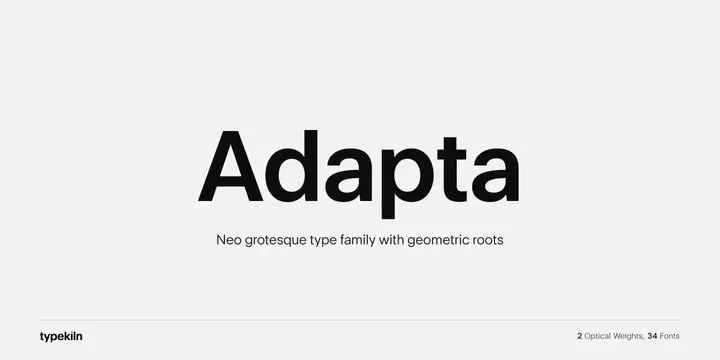
Adapta Sans Serif é uma família de fontes sans serif concebida para uso tanto em impressão quanto em produtos digitais. Esta fonte combina um estilo neutral com a elegância e personalidade únicas de formas geométricas, criando um design que transmite não apenas profissionalismo, mas também um toque acolhedor. Com uma ampla variedade de 34 tipos diferentes, incluindo duas opções de tamanho óptico distintas – Text e Display -, Adapta oferece versatilidade para criar textos variados que atendam a vários contextos. Os estilos de exibição, com espaçamento apertado, foram projetados para destacar títulos, enquanto os estilos de texto têm x-altura maior e aberturas mais largas, o que torna esses tipos altamente legíveis em formatos pequenos. Com essa combinação perfeita de design, funcionalidade e variedade visual, Adapta Sans Serif é uma opção perfeita para designers atentos às nuances de layout e conteúdo, buscando fontes que se destacam tanto no formato como na leitura de texto.